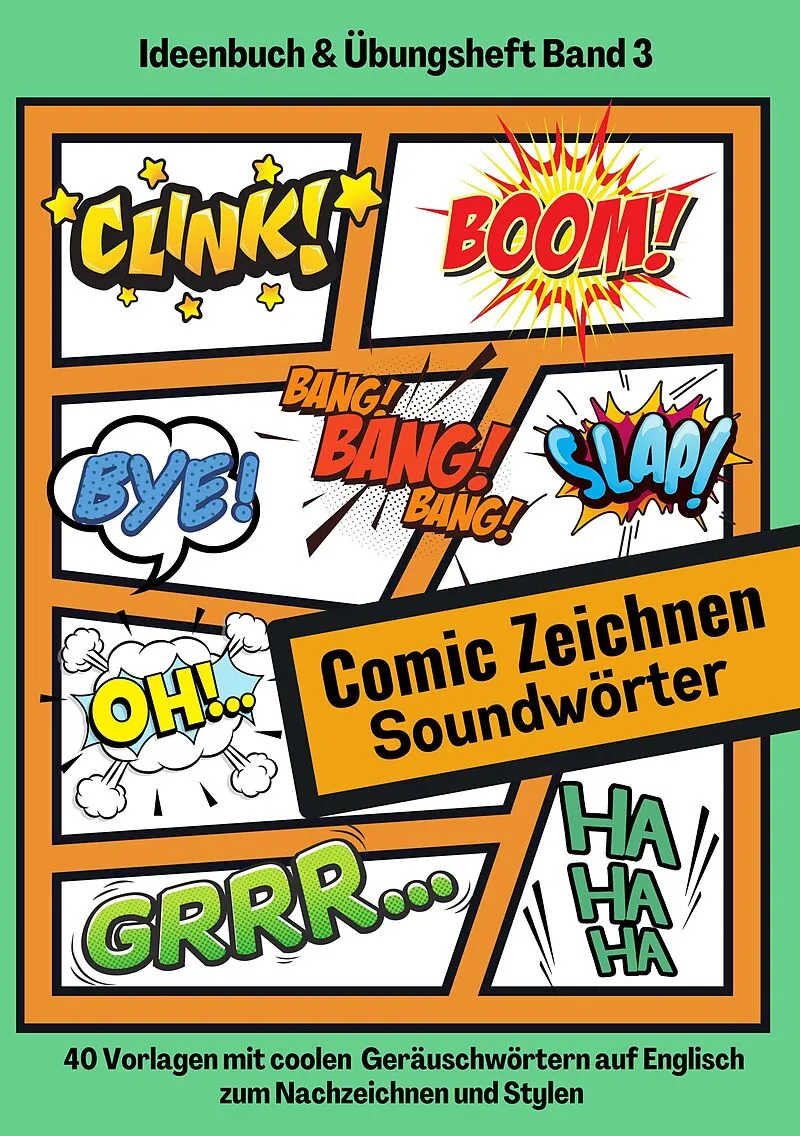
Comic Soundwörter zeichnen und kreativ gestalten Schriftarten Buchstaben Ideenbuch und Übungsheft für Kinder, Teenager, Erwachsene 40 Vorlagen mit coolen Geräuschwörtern auf Englisch
Zur Comic-Erstellung gehört die Darstellung von Sprech- und Denkblasen sowie Soundwörtern (Geräuschwörter). Mit diesem praktischen Übungsbuch wirst du deine Soundwörter-Kenntnisse vertiefen. Hier kannst du gezielt lernen, wie du Soundwörter auf Englisch kreat...